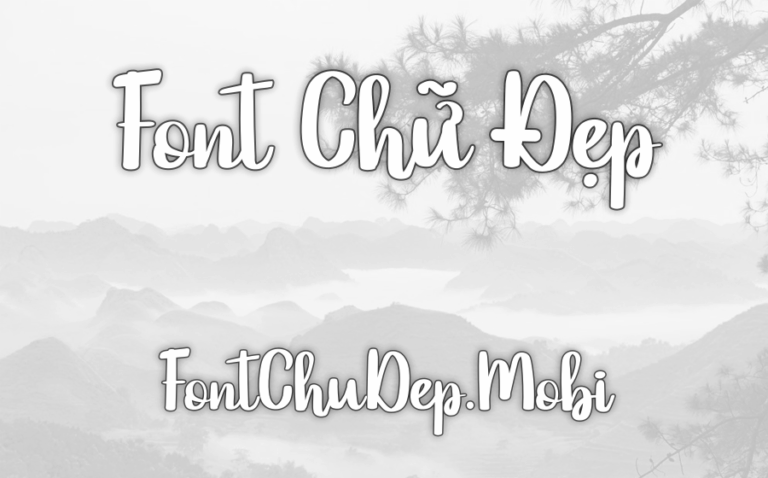
Font MTD Yolanda Princess Việt Hóa
Font MTD Yolanda Princess thật sự là một “viên ngọc quý” trong thế giới font chữ với phong cách viết tay nhẹ nhàng, tao nhã. Khi được trải nghiệm trực tiếp, tôi đã hoàn toàn ấn tượng bởi sự tinh tế và sự mềm mại của nó. Kiểu dáng calligraphy không chỉ đẹp mắt mà […]